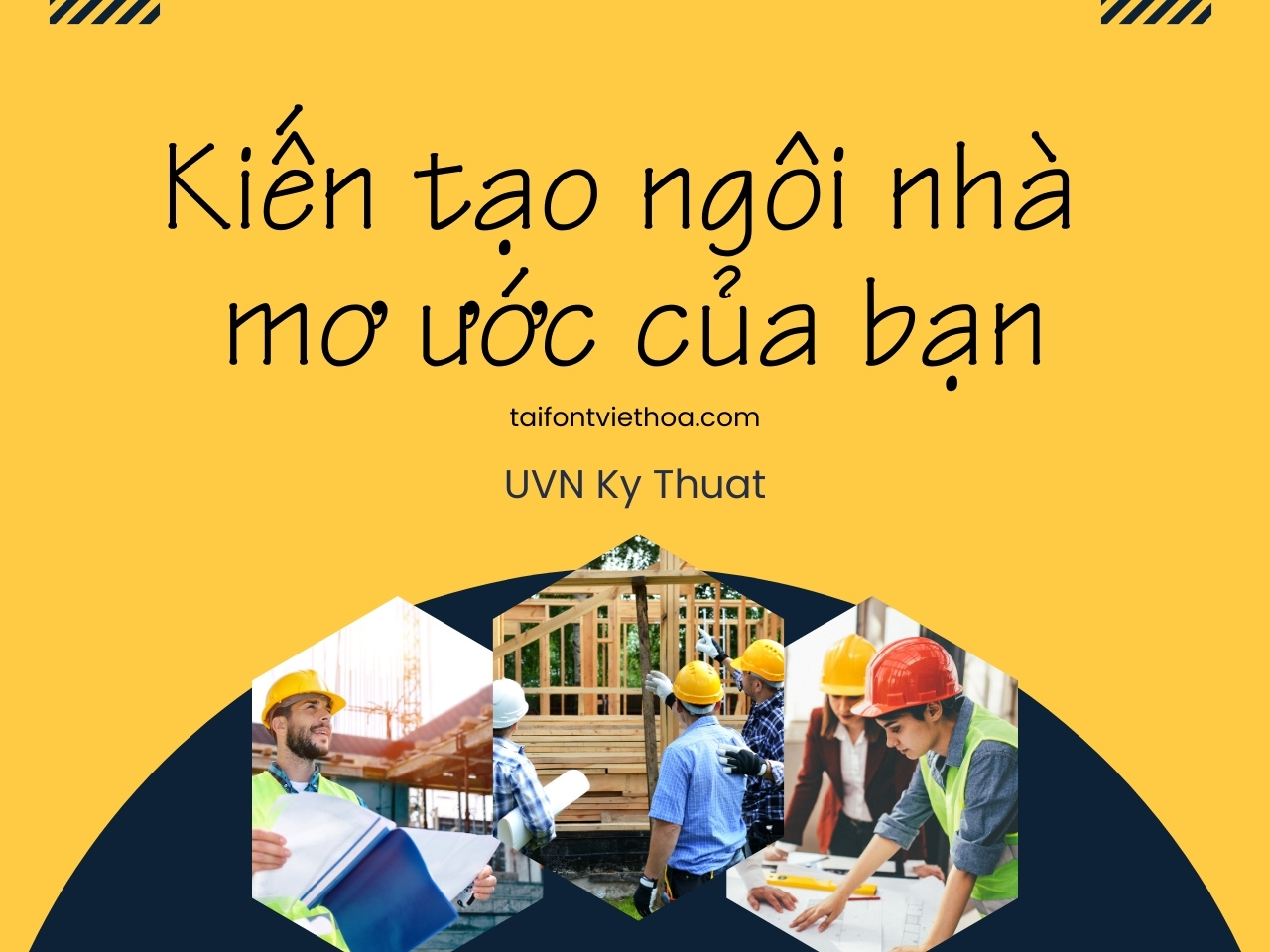
Giới thiệu về font UVN Ky Thuat
UVN Ky Thuat là một font chữ không chân (sans-serif) với kiểu dáng vuông vức, mạnh mẽ và rõ ràng, được thiết kế để phù hợp với các tài liệu kỹ thuật, bản vẽ, sơ đồ hoặc các nội dung mang tính chuyên môn cao. Phong cách thiết kế tối giản, không trang trí, giúp tăng khả năng đọc và thể hiện tốt tính chất nghiêm túc, khoa học trong trình bày. Font UVN Ky Thuat được sưu tầm và chia sẻ bởi thành viên Font Chuẩn, đồng thời được taifontviethoa.com chọn lọc kỹ càng để ứng dụng thực tế trong các dự án kỹ thuật, giáo dục STEM và thiết kế bảng biểu chuyên ngành.
Đặc điểm thiết kế và ứng dụng của UVN Ky Thuat
Font UVN Ky Thuat có cấu trúc chữ vuông gọn, độ dày đồng đều và độ tương phản thấp. Các ký tự dễ nhận diện, khoảng cách hợp lý giúp đảm bảo độ rõ ràng cao trên mọi nền tảng hiển thị. Đây là font lý tưởng để sử dụng trong bảng dữ liệu, tiêu đề kỹ thuật, chú thích bản vẽ hoặc thiết kế số hóa các tài liệu chuyên môn. Font hỗ trợ tiếng Việt đầy đủ và dễ dàng tích hợp trong phần mềm CAD, trình soạn thảo kỹ thuật hoặc hệ thống phần mềm nội bộ.
Ứng dụng lý tưởng: bản vẽ kỹ thuật, slide đào tạo kỹ thuật, bảng biểu tính toán, infographics chuyên ngành, giao diện phần mềm nội bộ. Ngành nghề phù hợp: công nghệ, kỹ thuật, xây dựng, cơ khí, phần mềm kỹ thuật, đào tạo STEM và quản lý sản xuất.